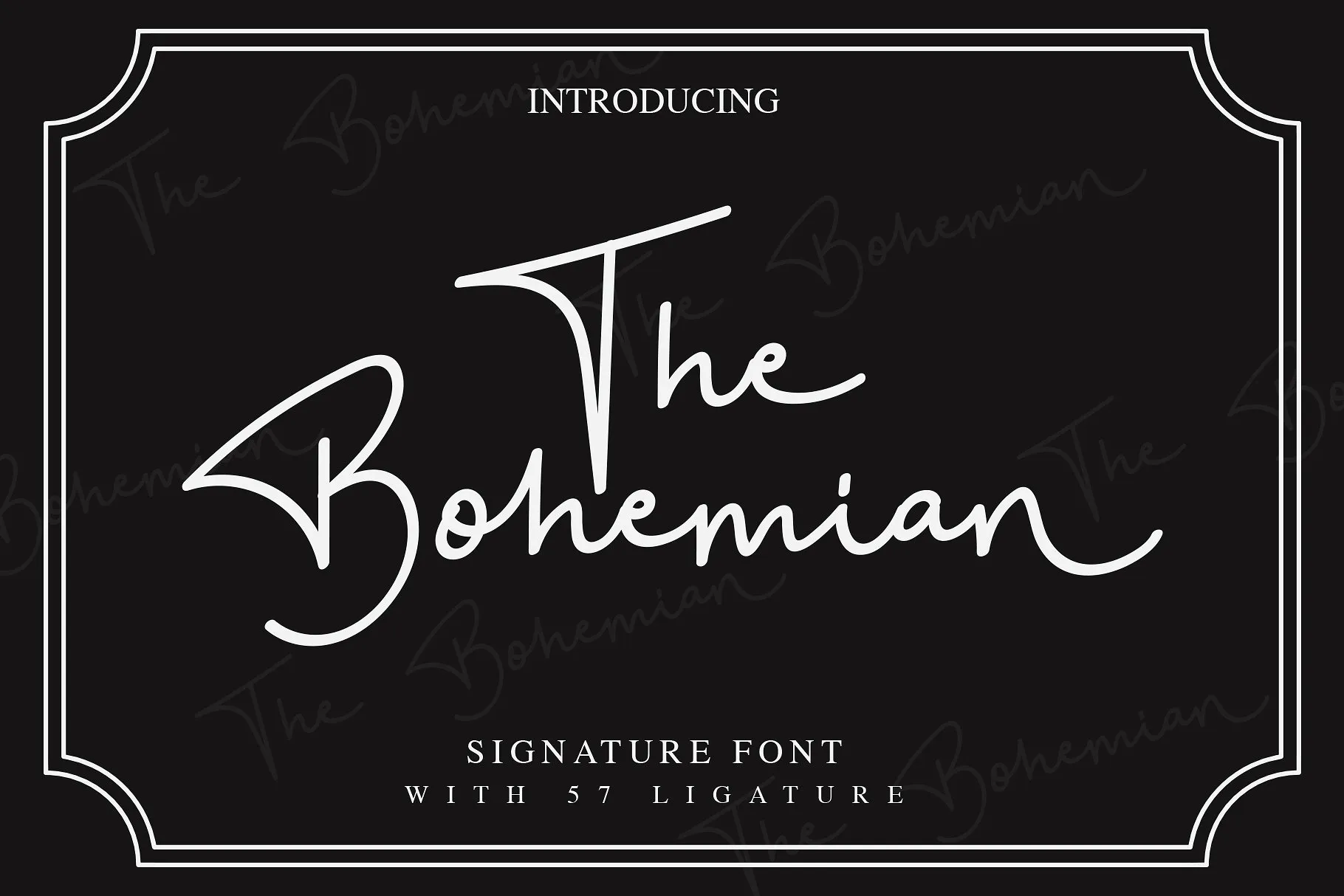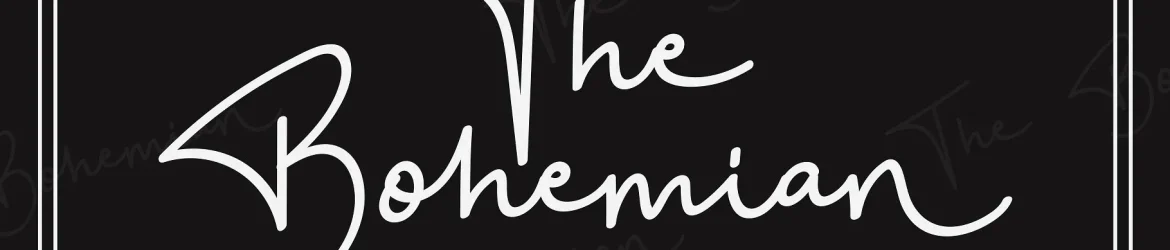
The Bohemian Signature Font – Download Grátis
Introduzimos a New Bohemian Signature Font, uma nova escolha para aqueles que buscam um estilo elegante e autêntico em suas criações digitais. Esta script-font é uma obra-prima de escrita manuscrita com um aspecto sofisticado e minimalista, perfeitamente adequada para projetos criativos como marcadores de água na fotografia, assinaturas ou logos de assinatura, citações, capas de álbuns e cartões de visita. A New Bohemian é uma fonte ideal para tornar seus trabalhos mais elaborados e chamativas, abrangendo um amplo espectro de projetos, desde os famosos cartões de visita até as marcadores de água na fotografia. Esta nova adição à nossa gama de fonts script não apenas reforça a qualidade do nosso design, mas também expande o seu potencial para incluir uma paleta mais diversificada e sofisticada em seus trabalhos.